Le manège équestre contemporain présente les mêmes formes et les mêmes décorations que la marelle antique, dont la création daterait donc des premiers temps d’une période dynastique de Haute-Égypte, la 17e dynastie qui importe les chevaux en tant que vecteur de guerre.
Il faut, pour appuyer cette idée, résoudre la question de sa transmission depuis les Égyptiens jusqu’à nous. Or ce n’est pas un secret, la civilisation Égyptienne fut, si ce n’est oubliée, tout au moins enfouie pendant longtemps.
Comment expliquer que nous utilisons des symboles Égyptiens disposés selon leurs croyances et leur philosophie ?
Comment émergent-ils en Europe et en lettres latines dans une société, dite post renaissance, s’intéressant aux grands classiques, mais ignorant le hiéroglyphique ?
Plusieurs lectures sont possibles.
Lecture Aléatoire.
Avec dix-sept caractères, il est possible de créer un nombre conséquent d’arrangements, c’est la factorielle de 17.
17 ! = 355 687 428 096 000
La combinaison exacte de notre manège possède deux chances, en fonction du sens de lecture, de tomber juste, c’est peu. C’est toutefois beaucoup plus que si l’on prend comme ensemble de départ les, pas loin de 800, signes hiéroglyphiques de l’époque ancienne.
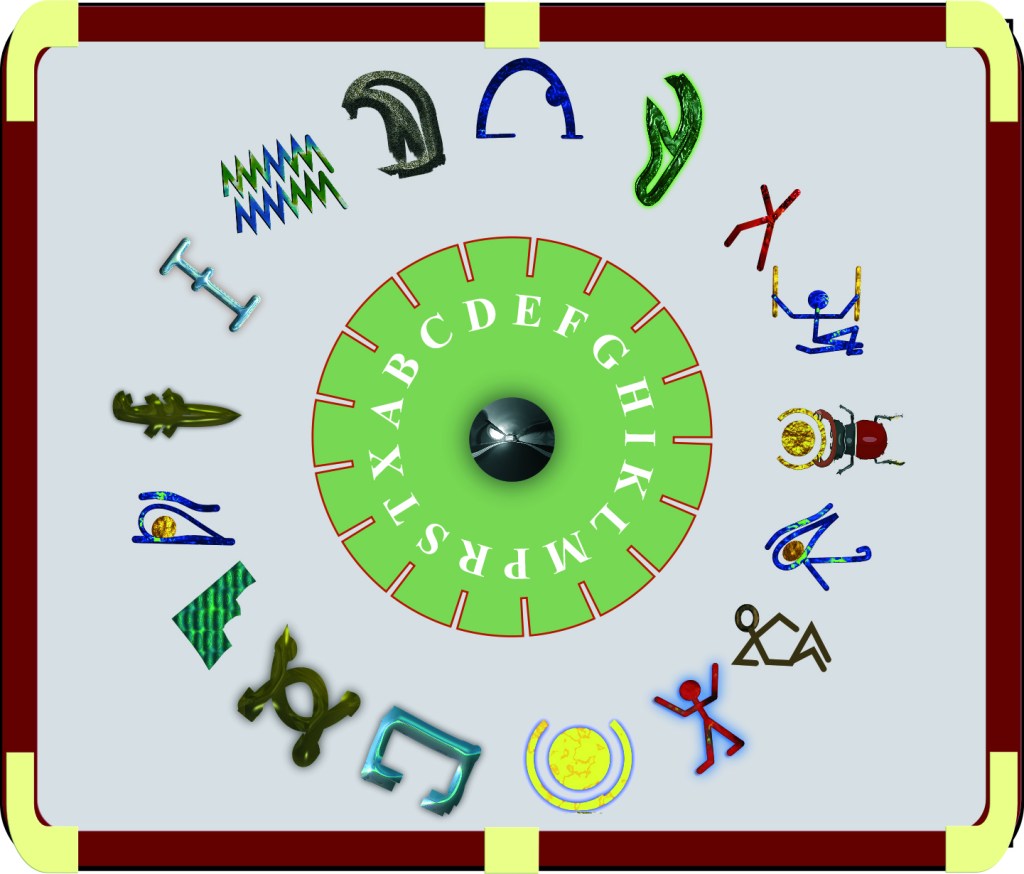
Alors il nous faut calculer la probabilité de tomber juste, en tirant 17 caractères parmi 800, dans l’ordre de la combinaison que nous connaissons. Cela fait beaucoup de cas, pour deux résultats probants.
L’organisation d’une surface d’entraînement équestre dotée de repères remarquables, placés de telle façon qu’ils célèbrent exactement la mystique Égyptienne et ses grandes valeurs, ne paraît donc pas être due au seul hasard, il s’agit d’une intention.
Pour autant celle-ci n’est pas forcément Égyptienne, elle pourrait émaner des utilisateurs successifs des écritures alphabétique.
Lecture Phénicienne
L’alphabet des origines qui nous a donné le Grec, l’Étrusque, le Latin, l’Araméen et autres dérivés, est le Phénicien. Le peuple des vaillants marins commerçants répand l’écriture facile autour de la grande bleue en quelques centaines d’années.
Chacune de leurs lettres est dotée d’une triple signification : graphique, pratique et symbolique. Pour les Phéniciens, un signe représente l’élément de base à assembler. Il est un objet ou un animal, une action, ou une intention.
On est troublé de constater les similitudes graphiques entre le hiéroglyphique linéaire très simplifié et les caractères Phéniciens, il faut pourtant noter des changements si profonds que leur sens s’en est trouvé transformé.
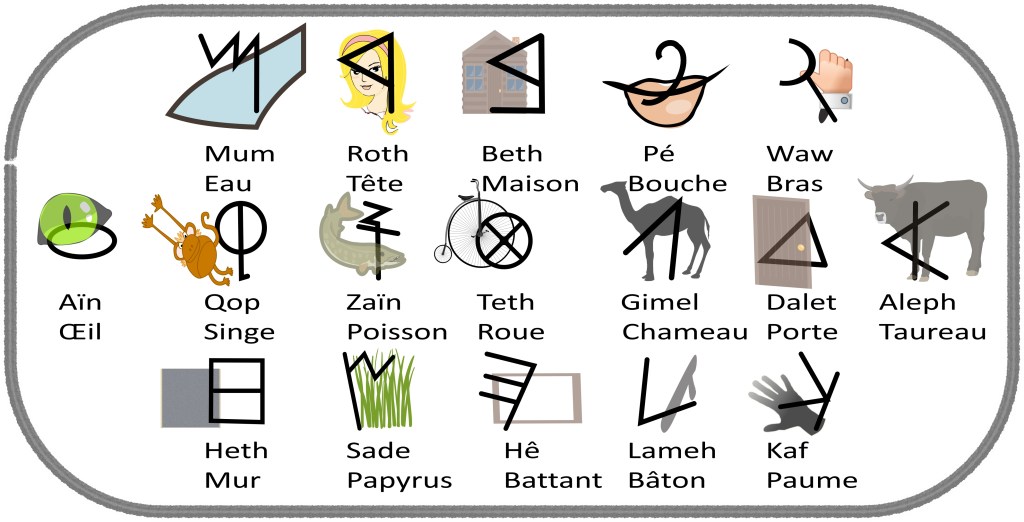
S’il n’y a pas de tracé racontant une genèse, suivant l’intention que lui donnaient les Égyptiens, il existe une marelle équestre Phénicienne utilisable autant comme un parcours de formation que support de jeu ou éventuel instrument à vocation mystérieuse, cela revient au même !
En reconstituant un « manège Phénicien », nous conservons l’aspect d’une marelle symbolique tout en perdant en puissance d’invocation, en force allusive et en logique, comme si les Phéniciens n’avaient pas besoin d’une copie servile des méthodes Égyptienne.
Faute d’une volonté guerrière impérialiste, ils n’ont pas créé durablement de force « inter cités » combattante. Leur activité était le troc, leurs vecteurs de transports les bateaux en Méditerranée et les caravanes sur quadrupèdes vers l’est et le sud.
Leur besoin de se constituer une cavalerie armée agressive était pourtant évident car cette région précise de la côte est l’objet de convoitises plurimillénaire la voyant successivement conquise puis reprise par la plupart des puissances proches, depuis les Assyriens aux Hittites en passant par les Egyptiens et les Perses.
Il existe pourtant des traces historiques convaincantes d’une armée « Phénicienne » dotée d’une cavalerie et attaquant des villes loin des côtes. Les guerres Puniques, de – 264 à – 146 concrétisent dans le sang l’opposition entre Rome et Carthage montrant des descendants de Phéniciens en bons cavaliers et en « cornacs » redoutables.
Lecture Grecque
Entre le Phénicien et le Grec ancien, les lettres pivotent sur leurs axes tout en restant reconnaissables. Avantage appréciable, elles conservent globalement leurs dénominations.
La conception est inchangée, elles ont depuis longtemps perdu leurs références divines Egyptiennes.
Il serait très tentant d’affecter aux lettres Grecques les sens profonds qui ont été appliqués aux Phéniciennes, au risque de commettre des erreurs et des anachronismes.
Comme les Grecs étaient des admirateurs et des connaisseurs de la culture Egyptienne, il serait tout aussi indiqué de regarder les similitudes avec cette dernière. De l’Alpha à l’Oméga, la ligne centrale encadre les éléments primordiaux, ce qui reste proche de la disposition Égyptienne, sans en re-calquer la prédominance solaire.
Français, Allemands, Anglais et écuyers de divers autres pays considèrent cette offre comme une aubaine. Ils vont être reçus, se formeront et diffuseront ensuite dans leurs pays les méthodes et avis des maîtres Napolitains, Ferrare Fiaschi, Federico Grisone et Giambattista Pignatelli, pour les plus célèbres.